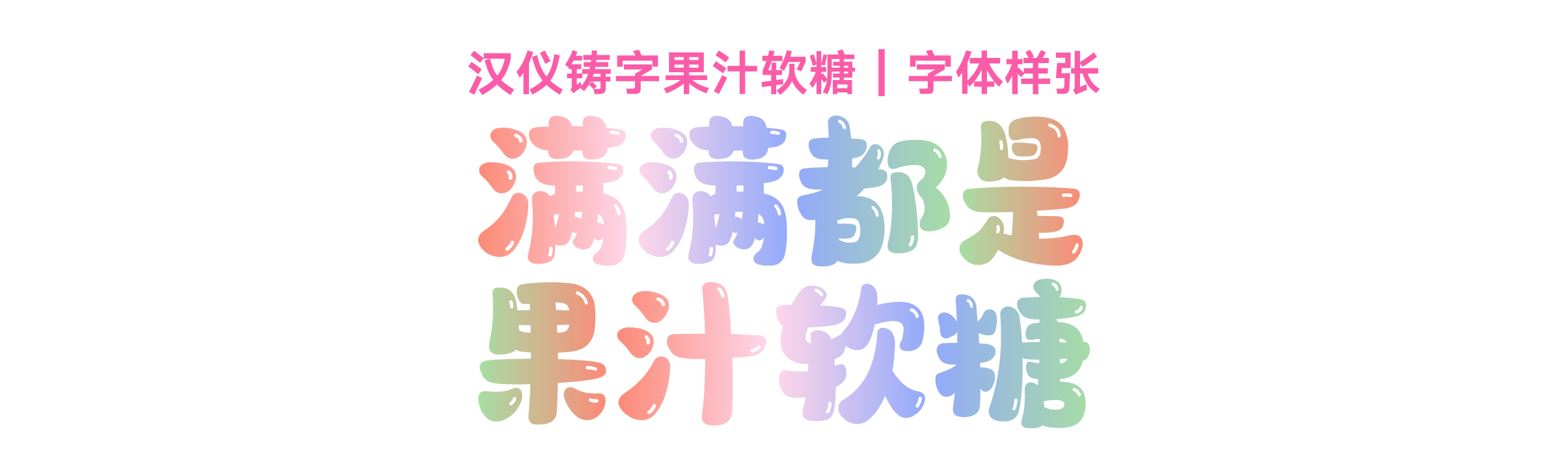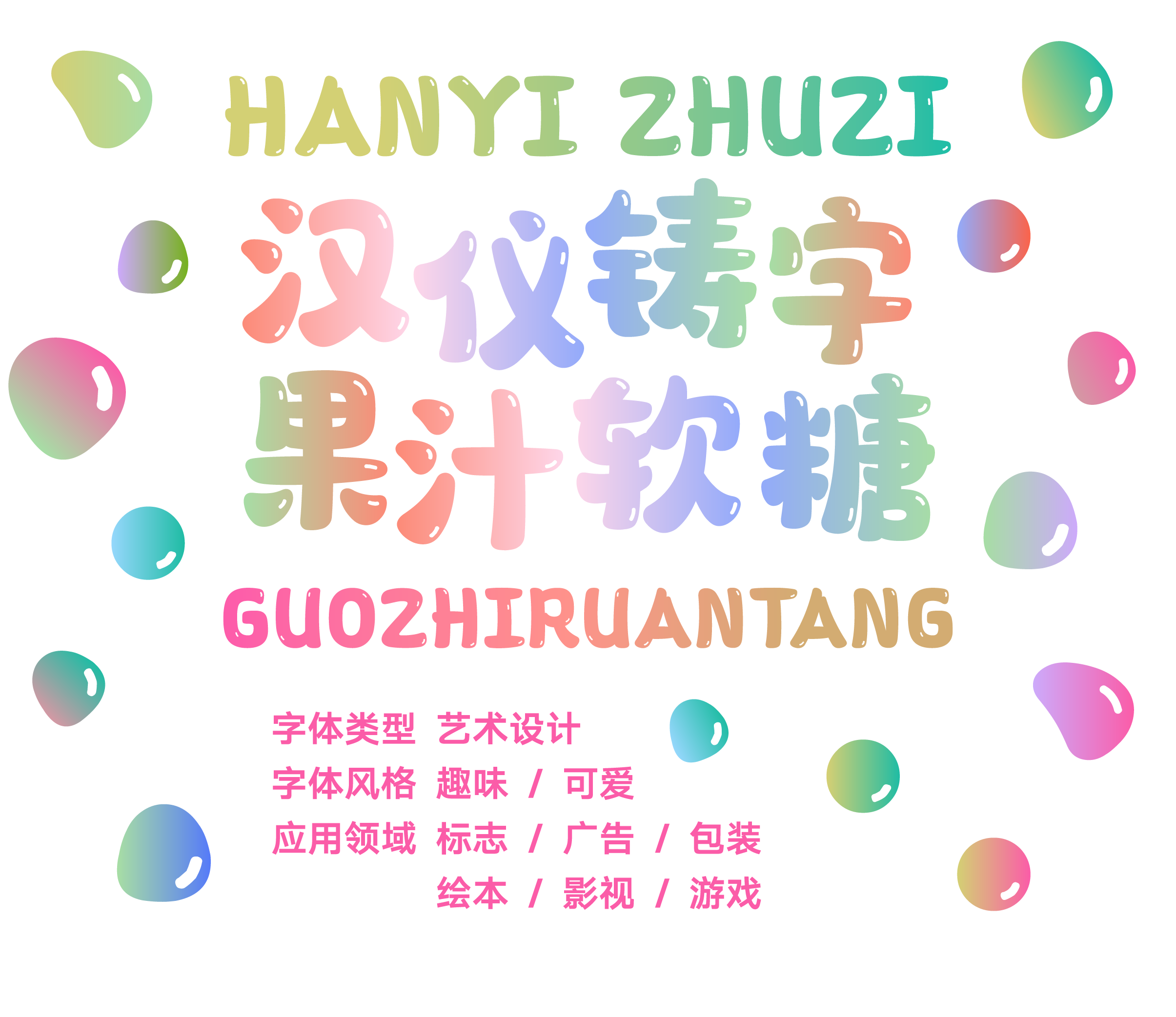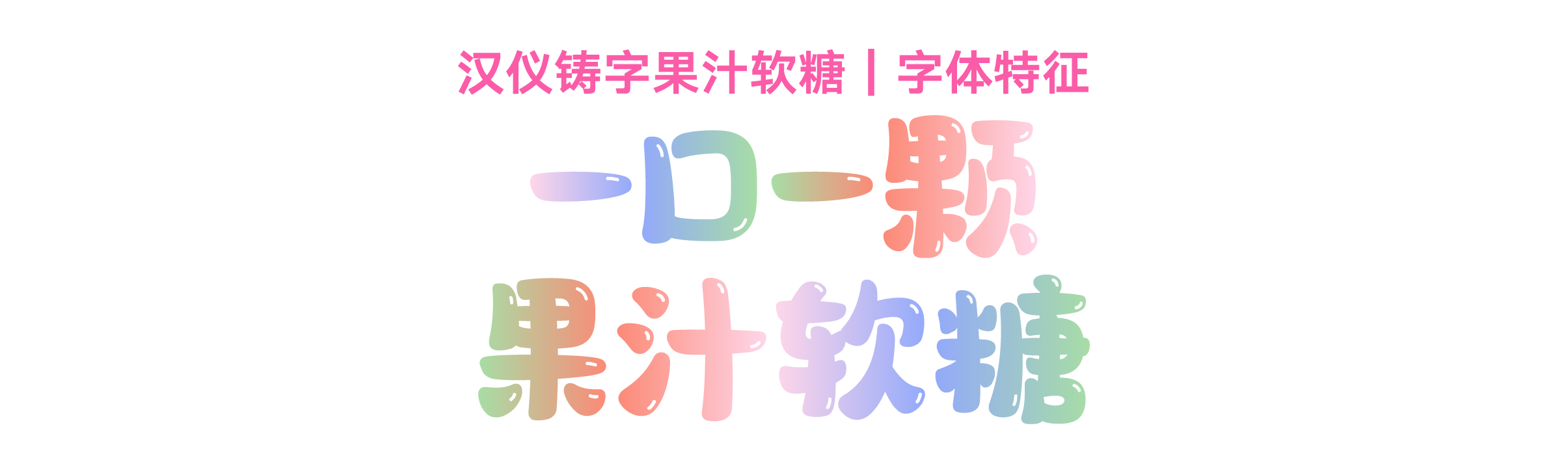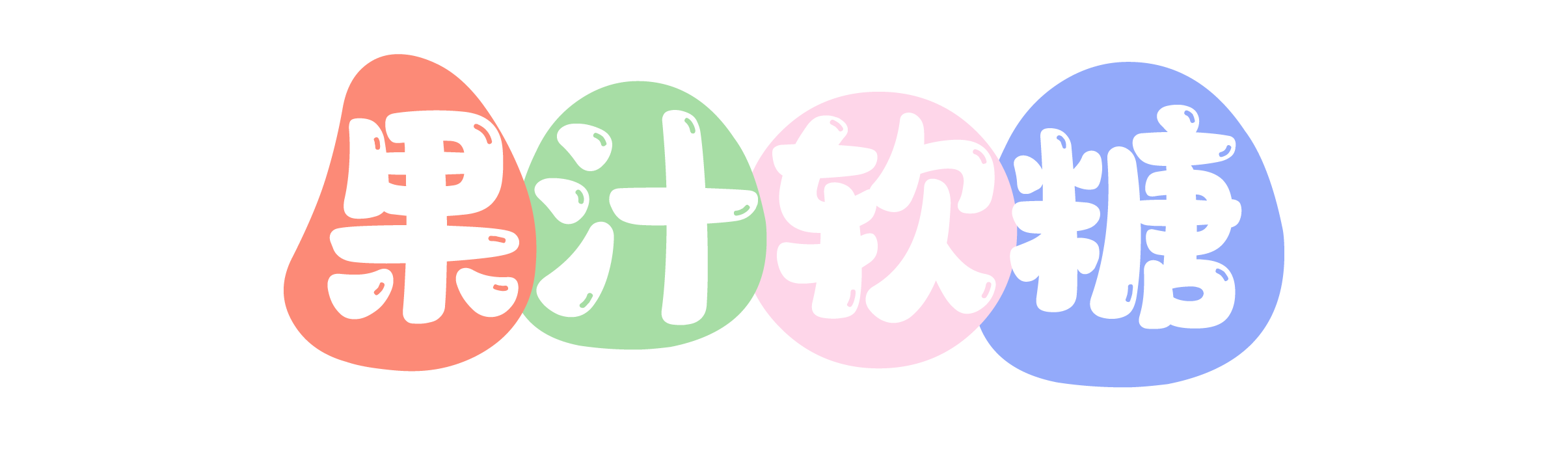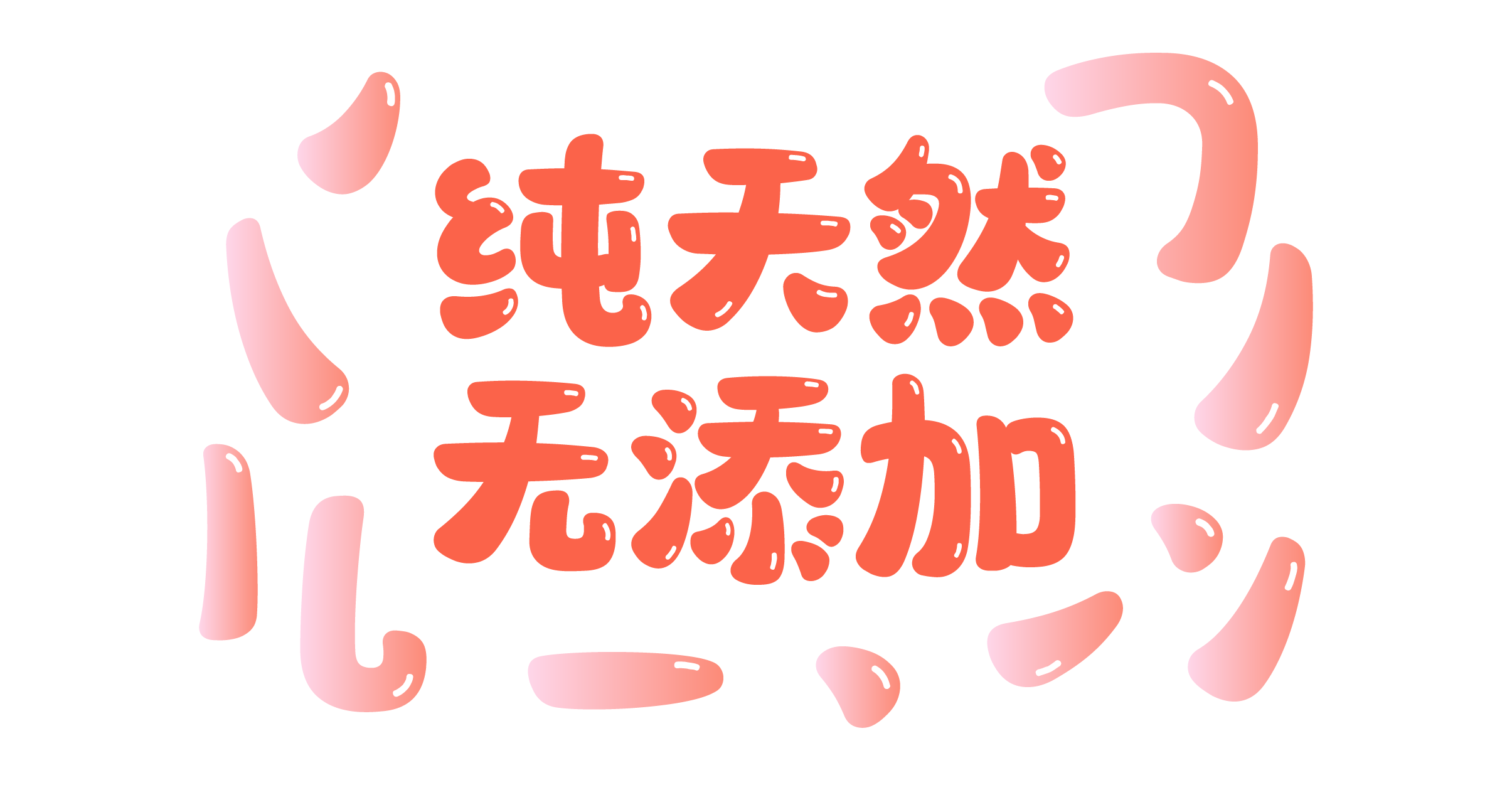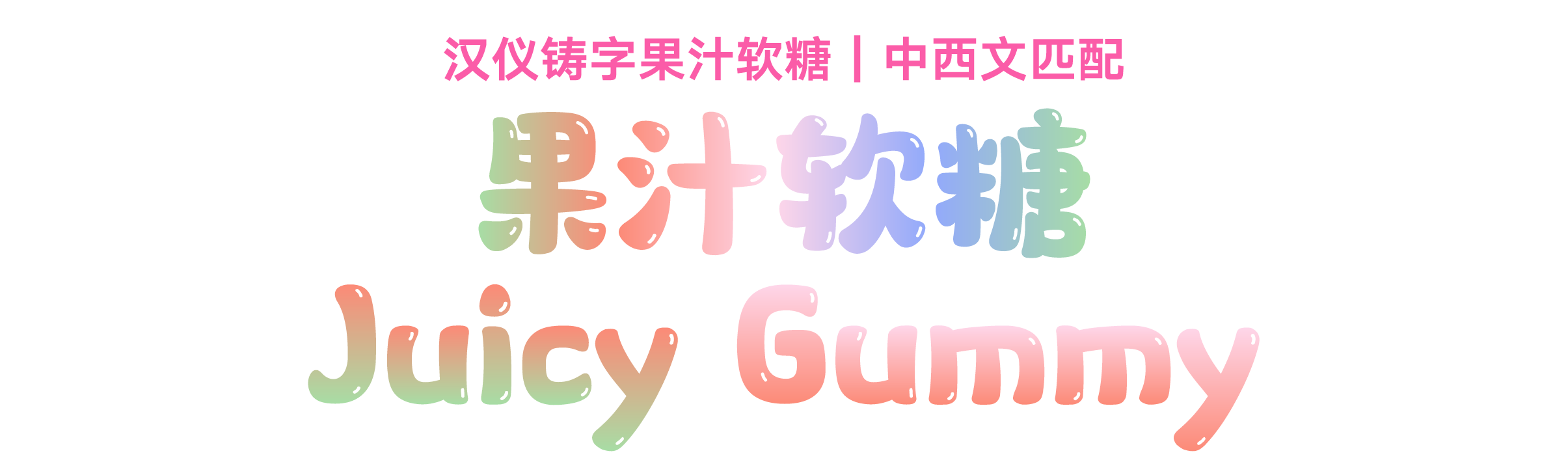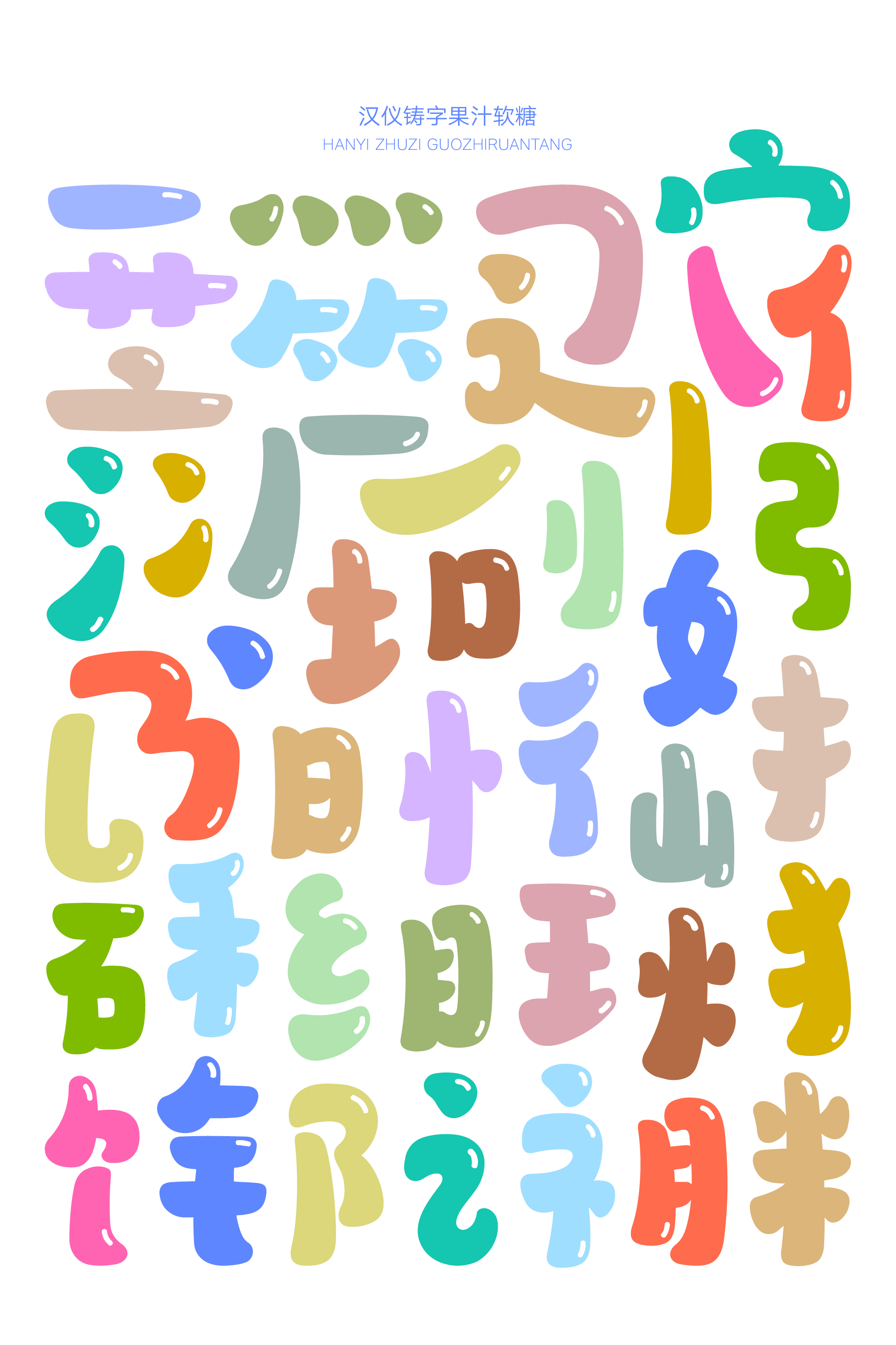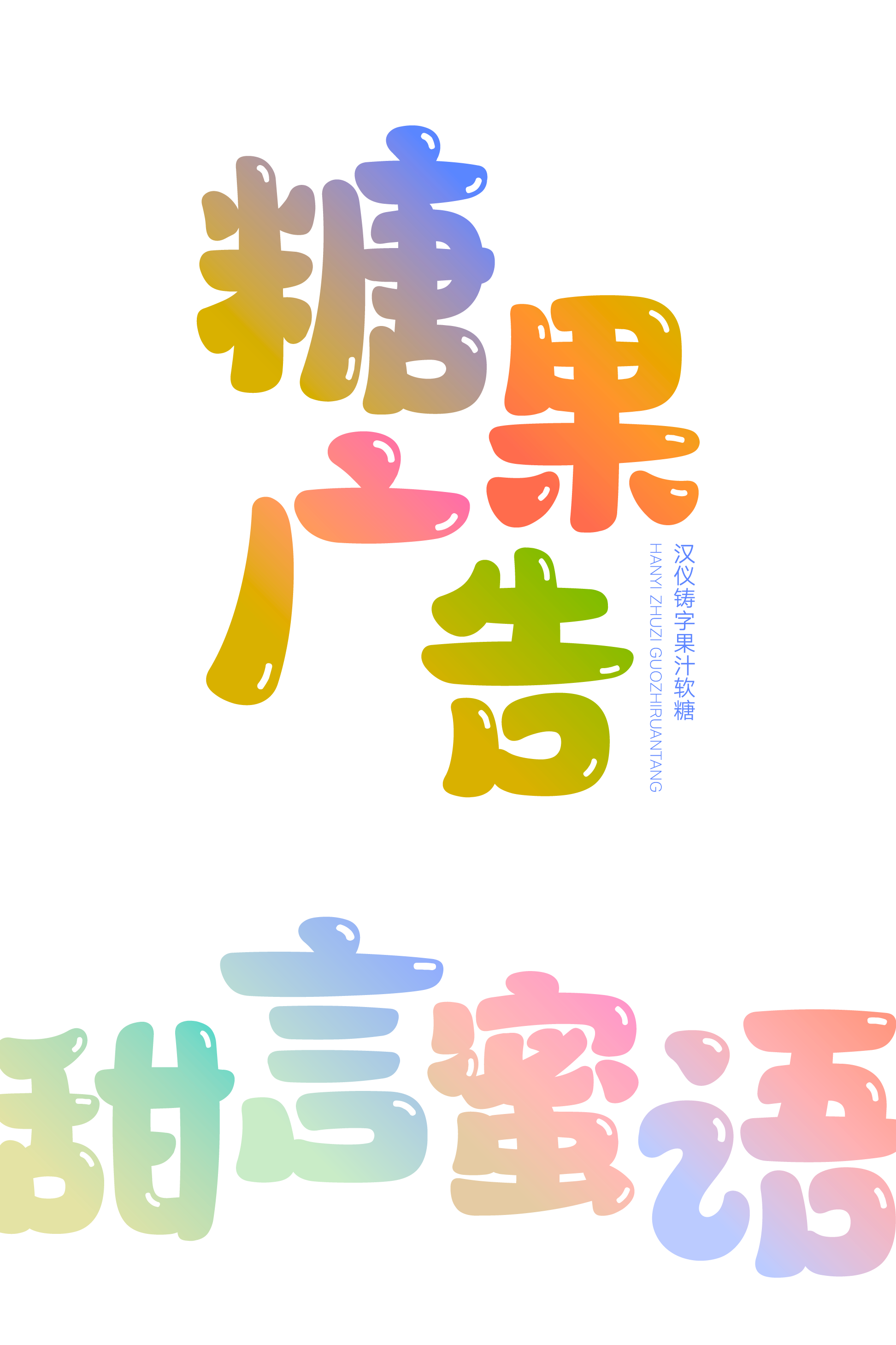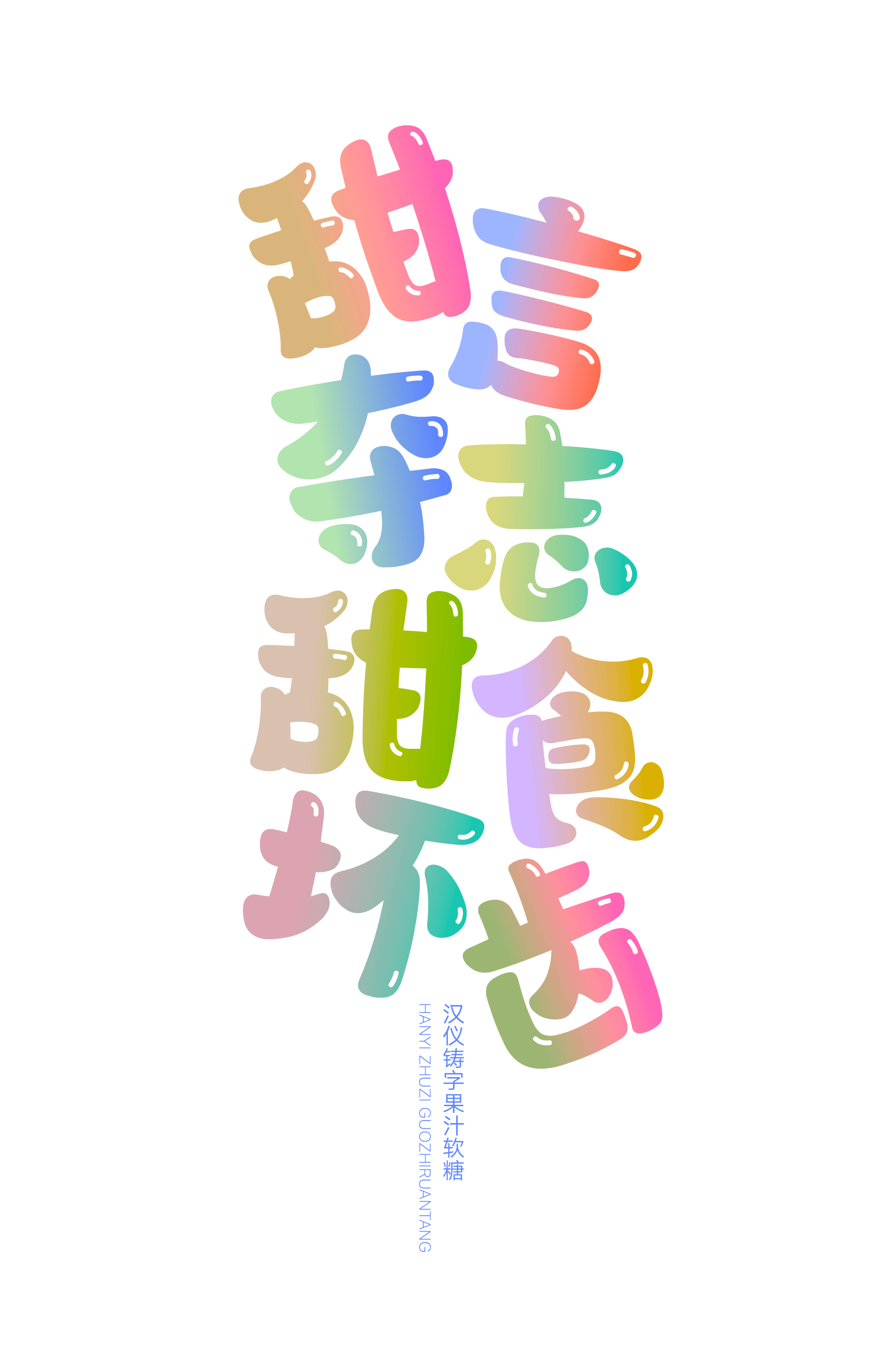
这款字体如果汁软糖般清爽有弹性
汉仪铸字果汁软糖,一口一颗,满满的快乐。这款字体俏皮活泼,好像有着柔软有弹性的口感和酸酸甜甜的味道,与缤纷的色彩搭配,可以带来丰富的视觉体验。不论是作为标题字体引人注目,还是用于短文本排版点缀画面,汉仪铸字果汁软糖都可以蹦蹦跳跳地表现出果汁软糖般地清爽软弹。
字形俏皮可爱,像是一颗一颗的果汁软糖。
富有弹性的笔画还原了果汁软糖柔软有嚼劲的口感。
笔画高光点缀了果汁软糖的晶莹质地。
西文部分是略长的软糖造型,柔软、饱满、有弹性,中西文搭配使用就像是打开一罐色彩形态多变的果汁软糖,满满的都是快乐。